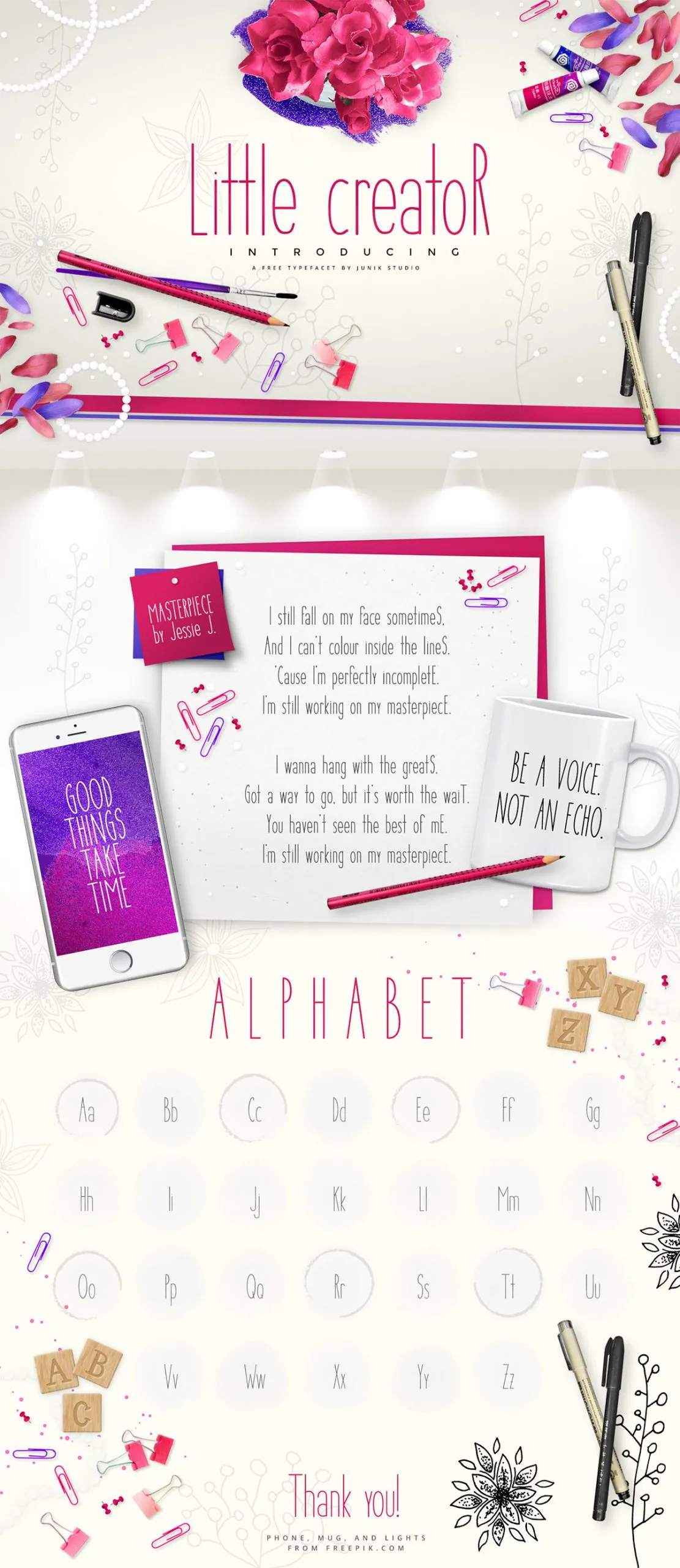
A Little Creator Font é uma fonte sans-serif criada pelo designer Hamilton. Ela oferece letras maiúsculas e minúsculas, números e caracteres básicos para ajudar no seu design de layout. Esta fonte é gratuita, o que torna ela ainda mais acessível aos designers e ilustradores que estão sempre à procura de recursos gráficos variados em um orçamento limitado. Suas linhas retas e minimalistas se combinam perfeitamente com qualquer tipo de projeto visual, seja para criar um layout agradável ou desenvolver uma série de caracteres único para sua marca. Uma fonte dessa qualidade é um grande investimento para seu armário personalizado de recursos, e o Little Creator não é exceção.